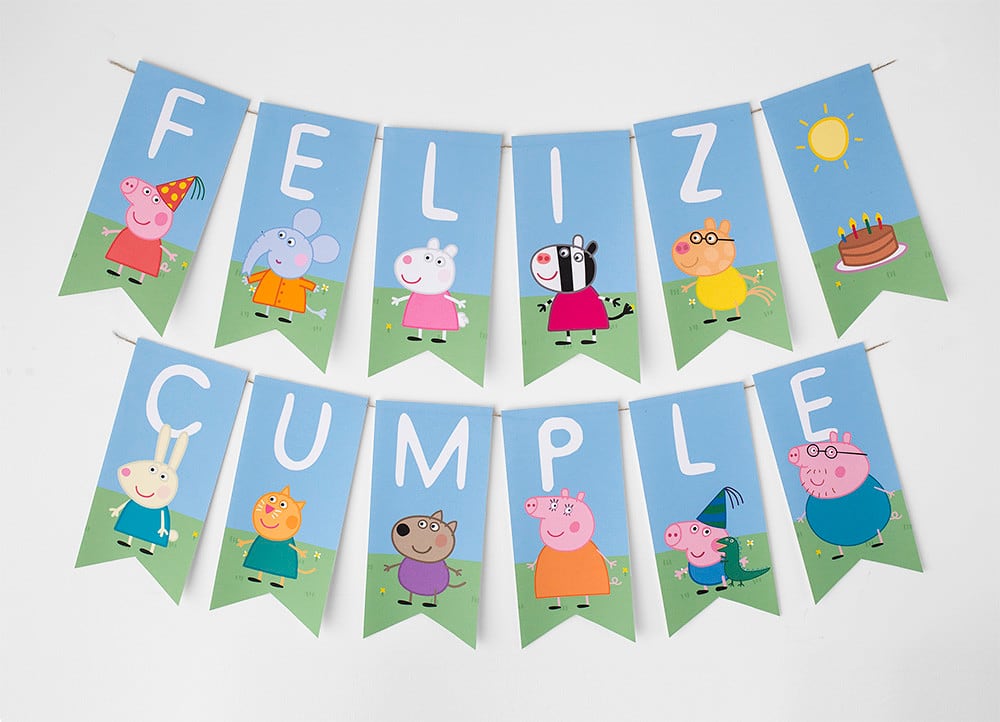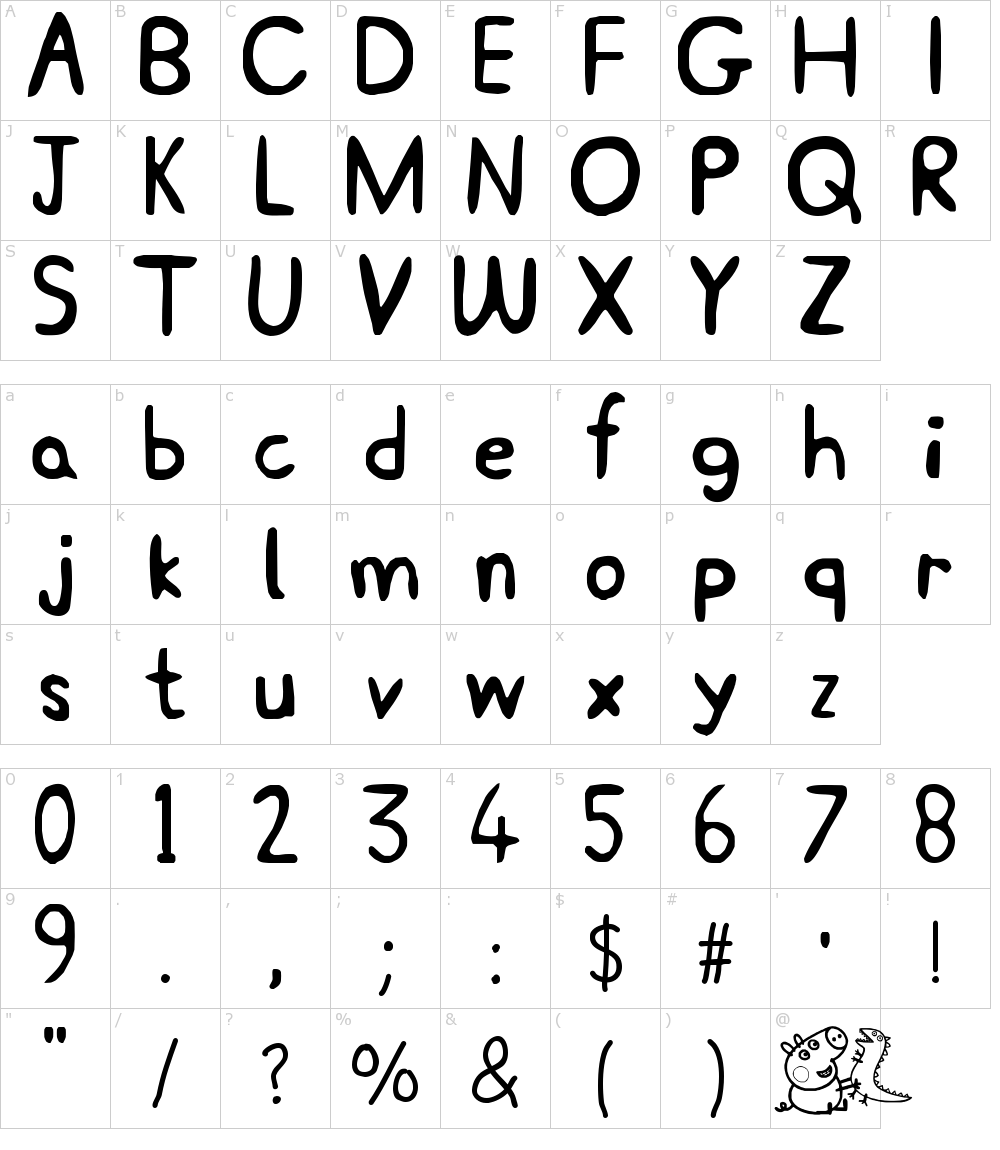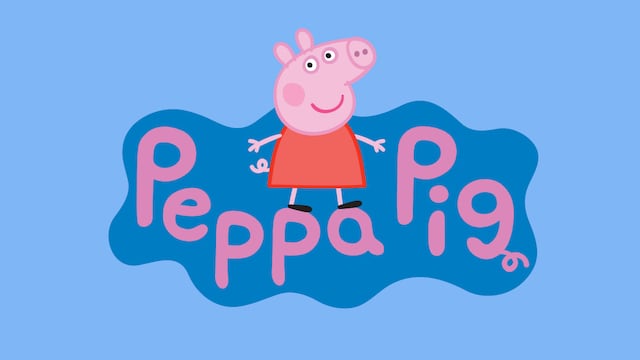
Descarga la tipografía de Peppa Pig y celebra la mejor fiesta infantil con el paso a paso que te tenemos.
Si estás a punto de tener una fiesta infantil y el personaje central es Peppa Pig, sin duda esto te interesa.
Pues te tenemos la tipografía de Peppa Pig para que cuides hasta el último de los detalles para esa esperada fiesta infantil.
¿Qué tipografía es la que utiliza Peppa Pig?
La tipografía que utiliza Peppa Pig es única, ya que se trata de un diseño propio de la popular caricatura.
Dicho esto, la tipografía que utiliza Peppa Pig se caracteriza por sus letras grandes tipo escritura libre.
Con formas ovaladas definidas, así como en su grosor de cada letra; su color predilecto de tipografía que utiliza Peppa Pig es el rosa y con un fondo en azul.